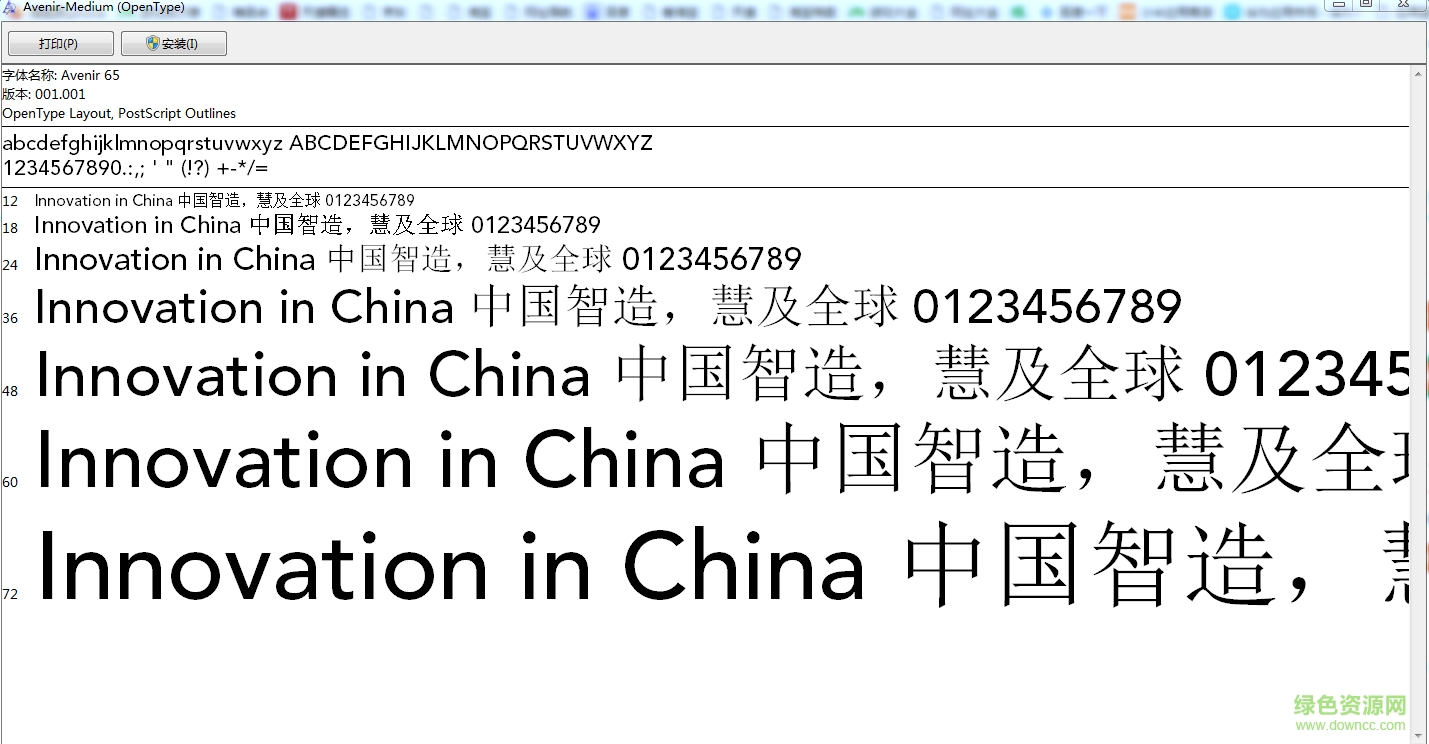
avenir medium
avenir medium字體是一款中等粗細(xì)的字體,結(jié)構(gòu)飽滿,線條柔和,粗/細(xì)過渡得當(dāng),用于書、報刊印刷、廣告宣傳、包裝裝飾等效果都很好,有需要的朋友快來綠色資源網(wǎng)下載吧!
現(xiàn)代字體風(fēng)格
穩(wěn)重挺拔。字體造型規(guī)整,富于力度,給人以簡潔爽朗的現(xiàn)代感,有較強(qiáng)的視覺沖擊力,這種個性的字體,適合于機(jī)械科技等主題。